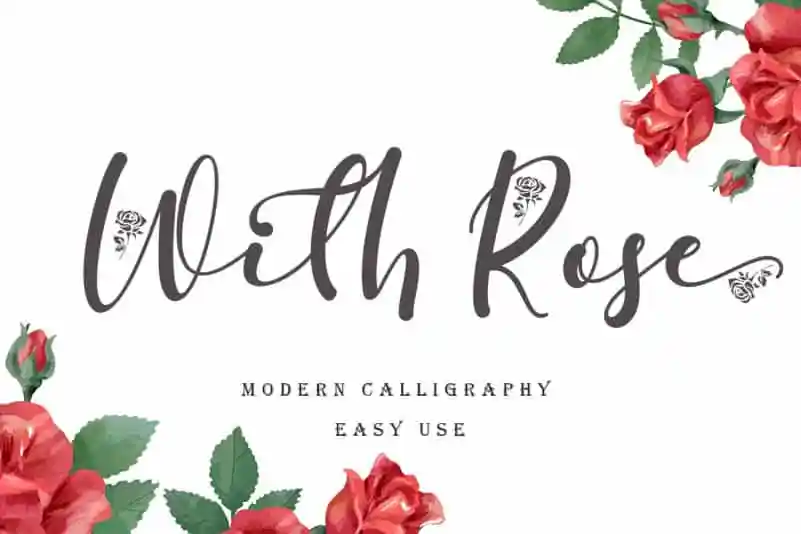
With Rose Script Font – Download Grátis
A fonte With Rose Script é uma escolha ideal para quem busca um estilo elegante e sofisticado. Desenvolvida especificamente para atender às suas necessidades criativas, esta fonte foi projetada com letras claras que são fáceis de manusear. Além disso, ela se destaca por sua facilidade em transformar palavras simples em textos bonitos e atraentes. Com seu design cuidadosamente feito para atender aos mais variados usos, esta fonte é perfeita para eventos como casamentos, datas especiais e campanhas promocionais. Também se adapta bem à criação de logotipos, identidade visual e materiais publicitários. A With Rose Script também destaca-se em plataformas digitais, desde redes sociais até banners e posters. Ela é uma excelente opção para quem procura personalizar seu conteúdo com um toque elegante e sofisticado. Sua simplicidade e beleza fazem desta fonte um recurso indispensável para qualquer designer gráfico, seja no formato digital ou impresso. Com a With Rose Script, você pode adicionar um toque de luxo à sua produção visual, tornando-a mais atraente e envolvente.